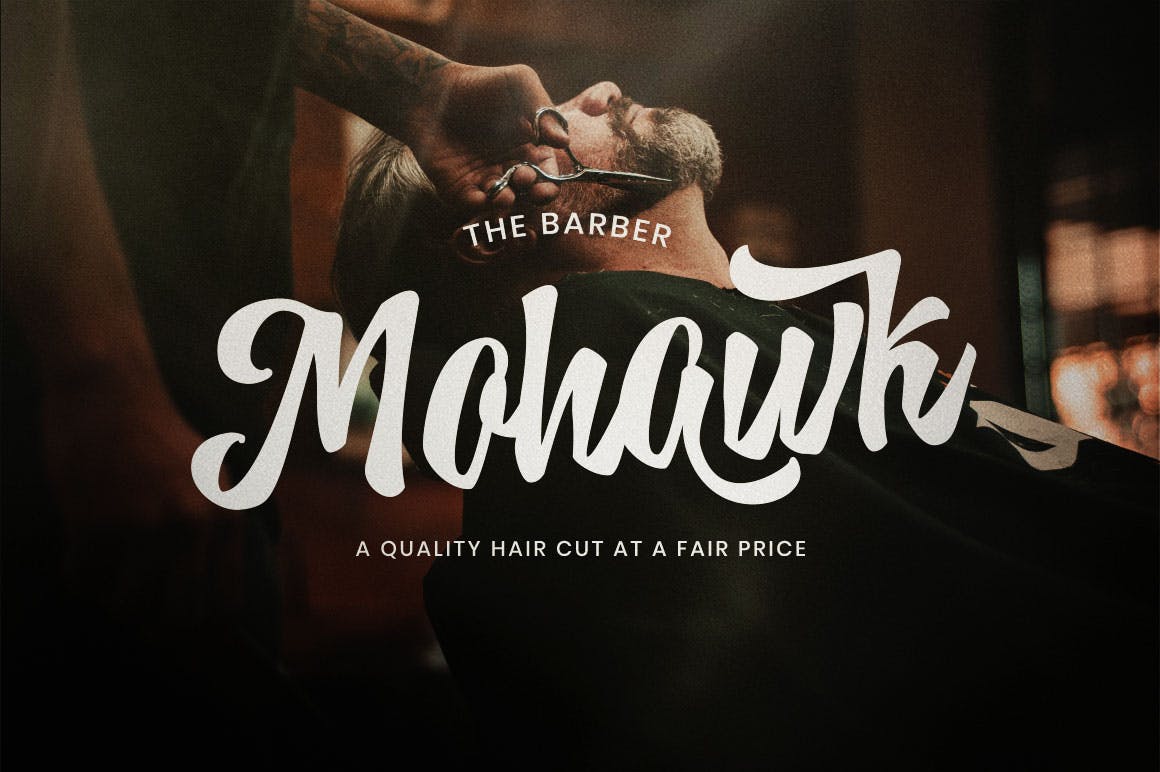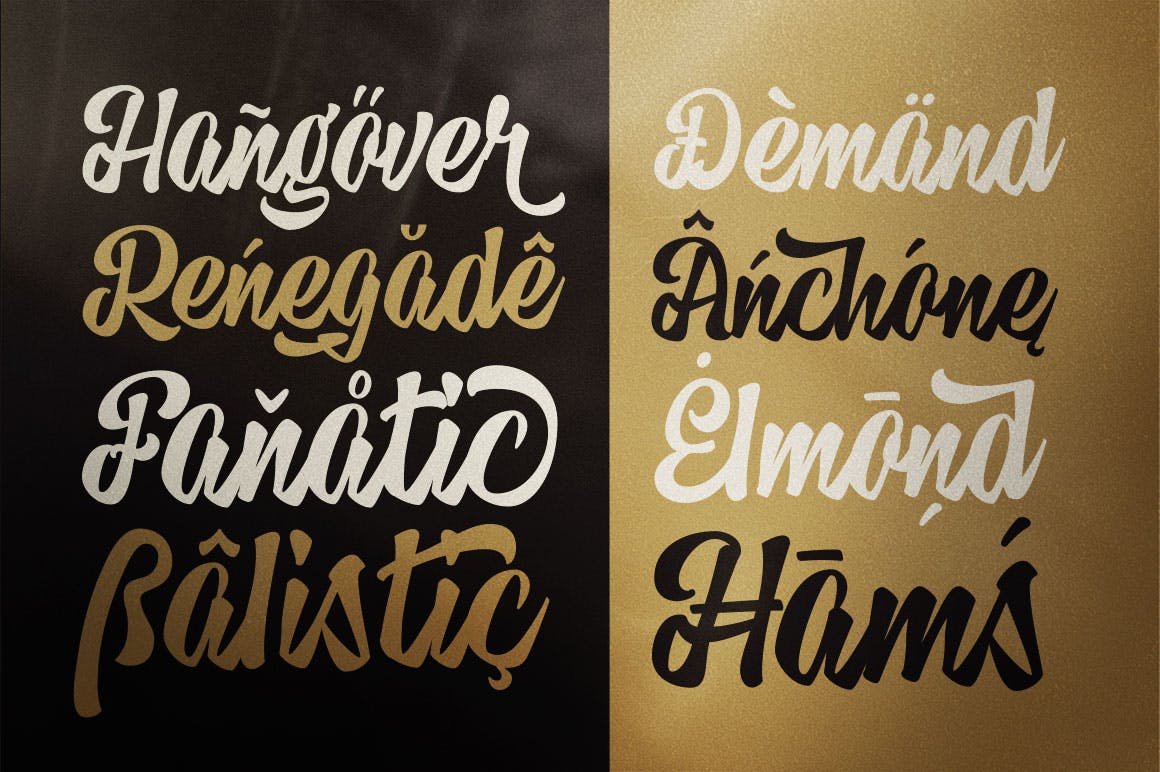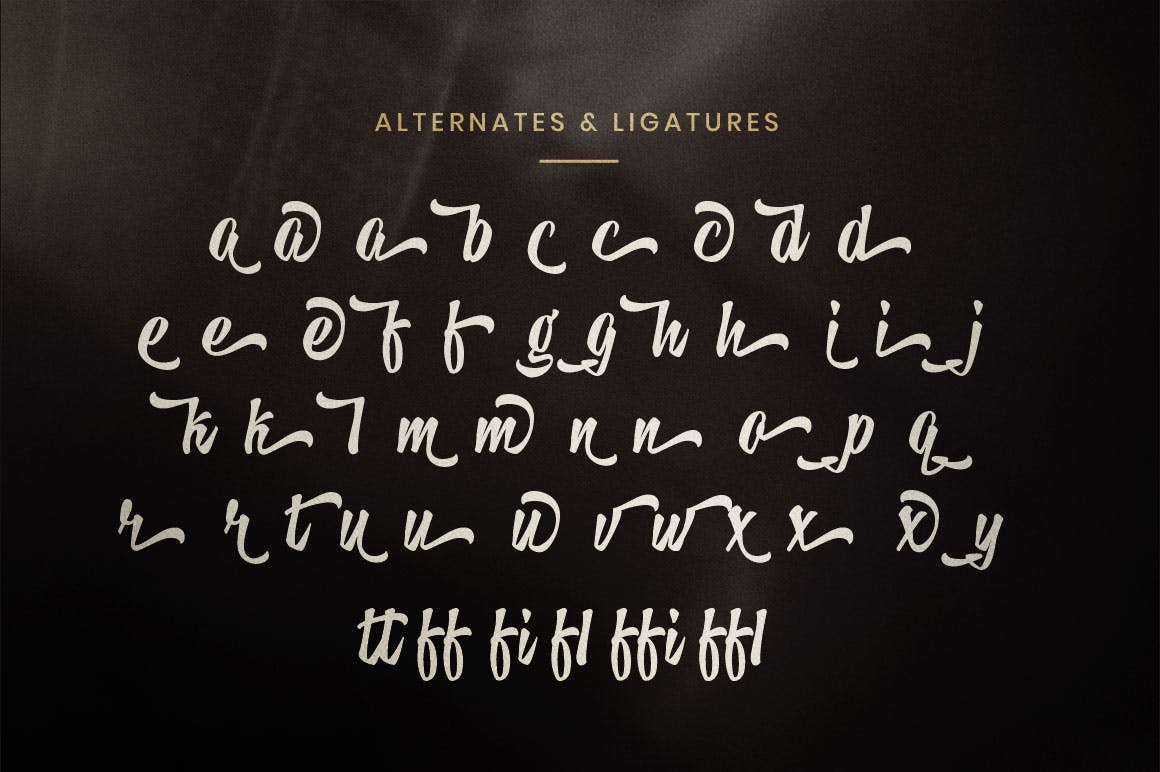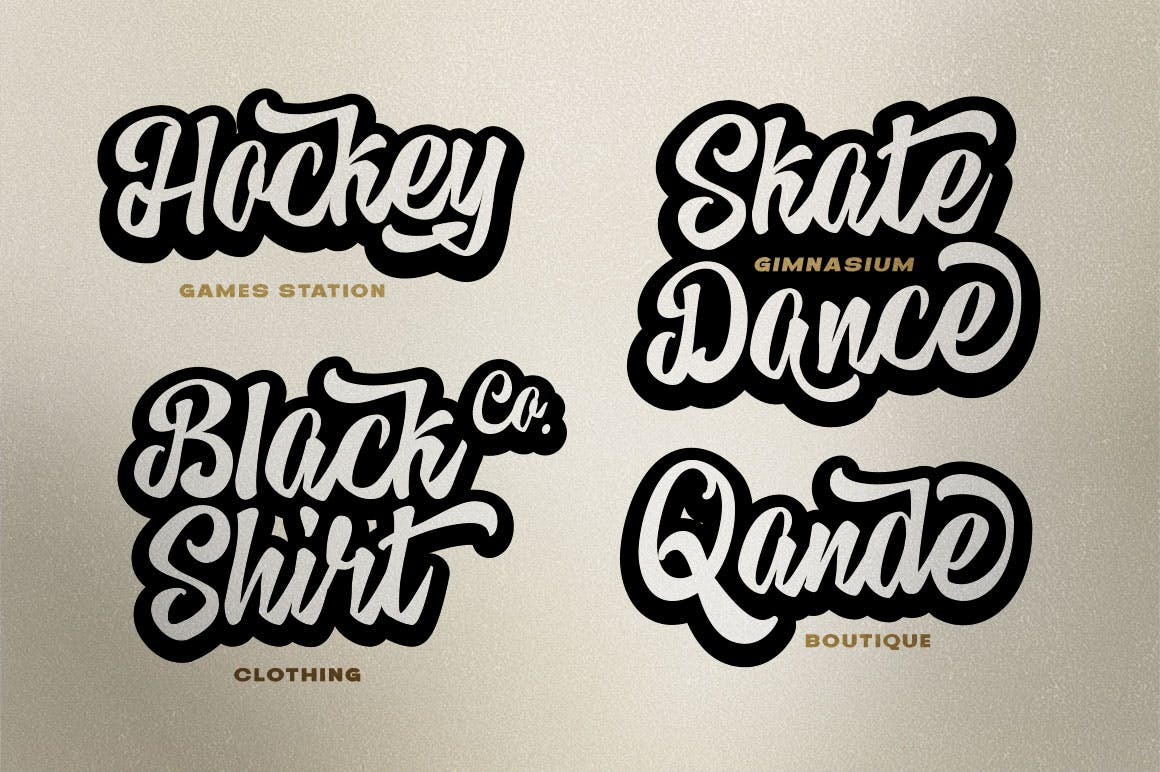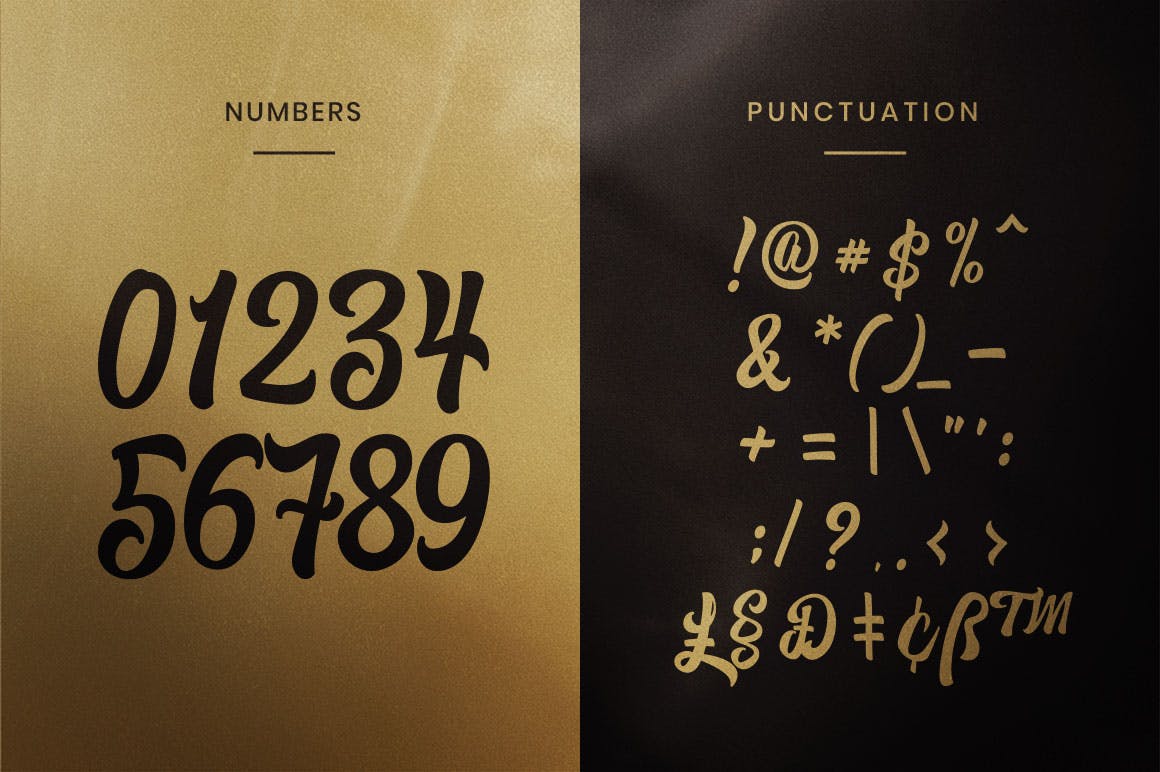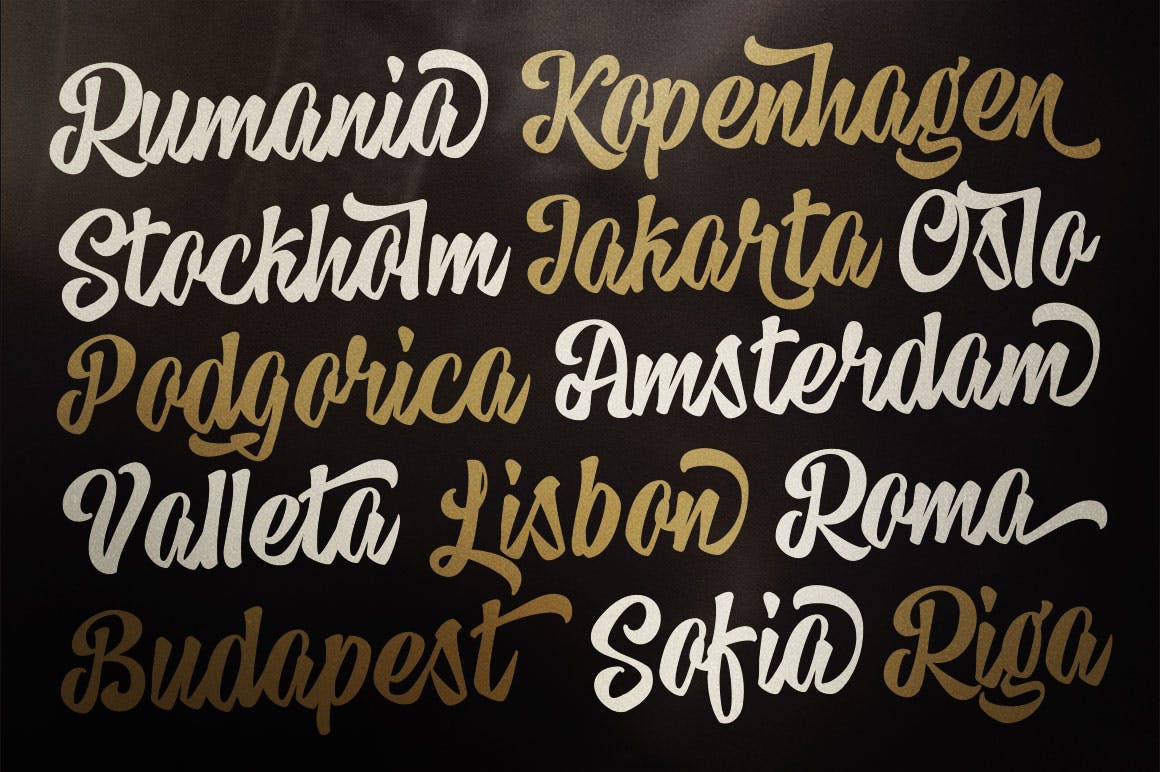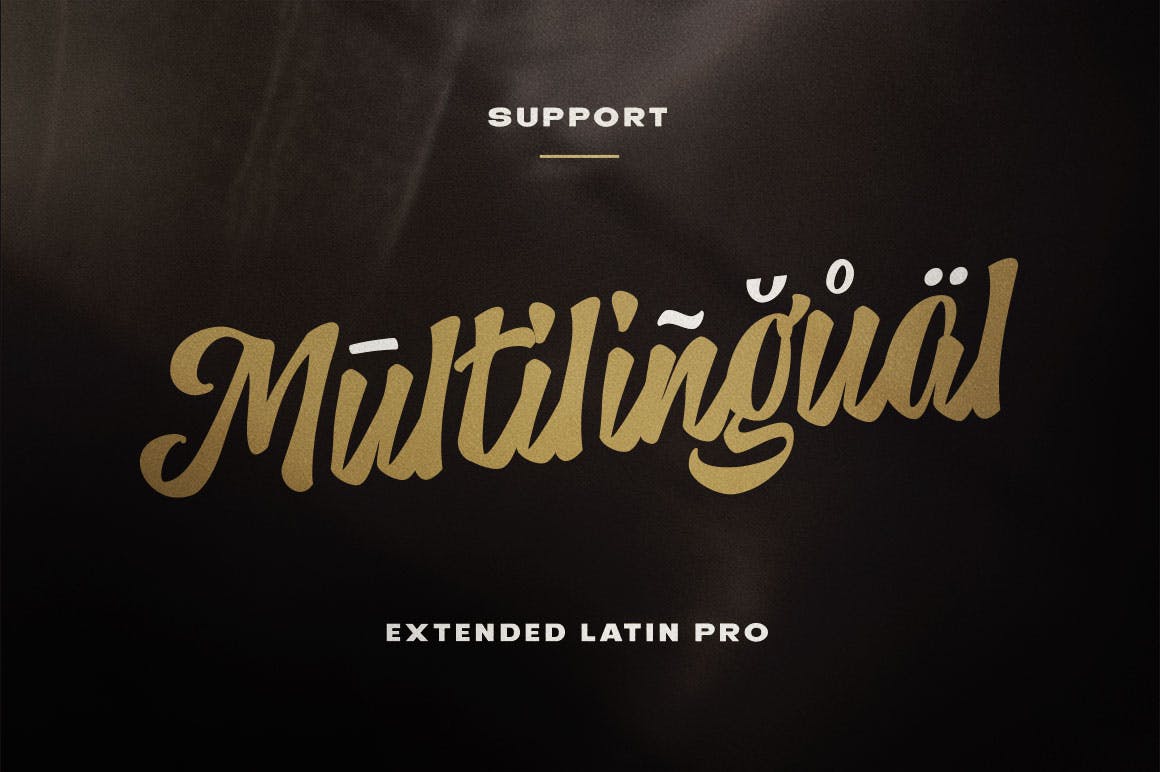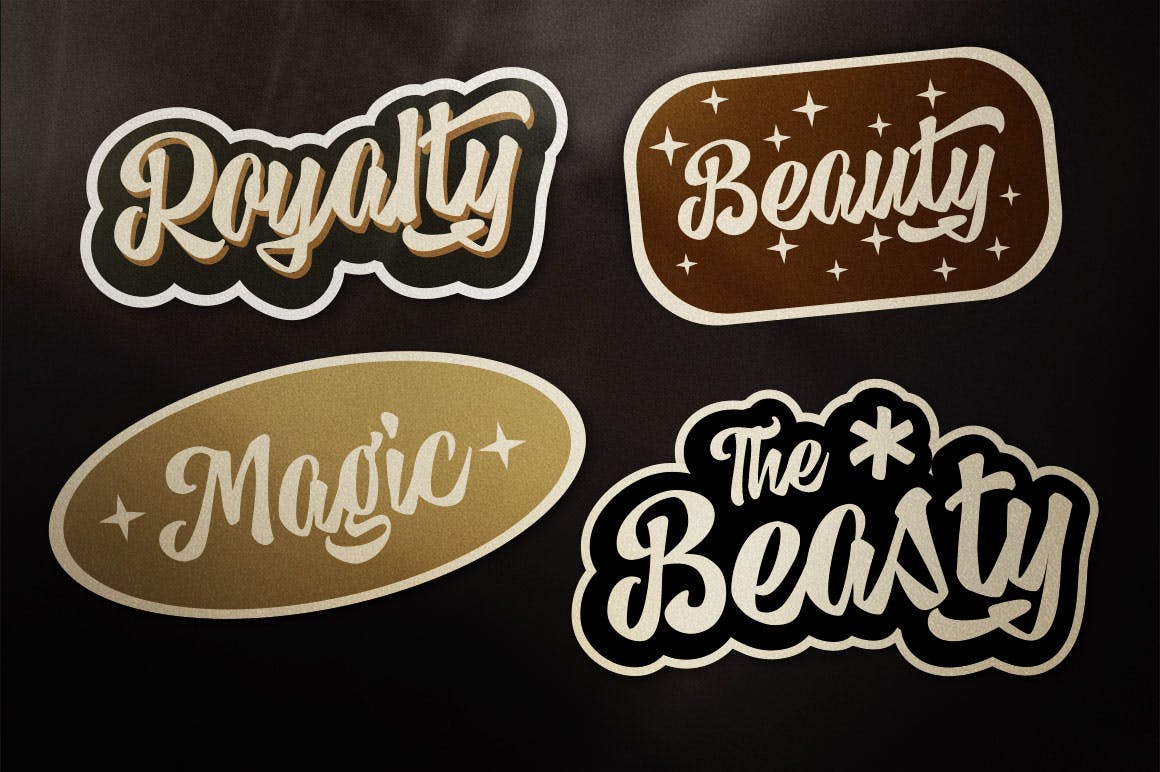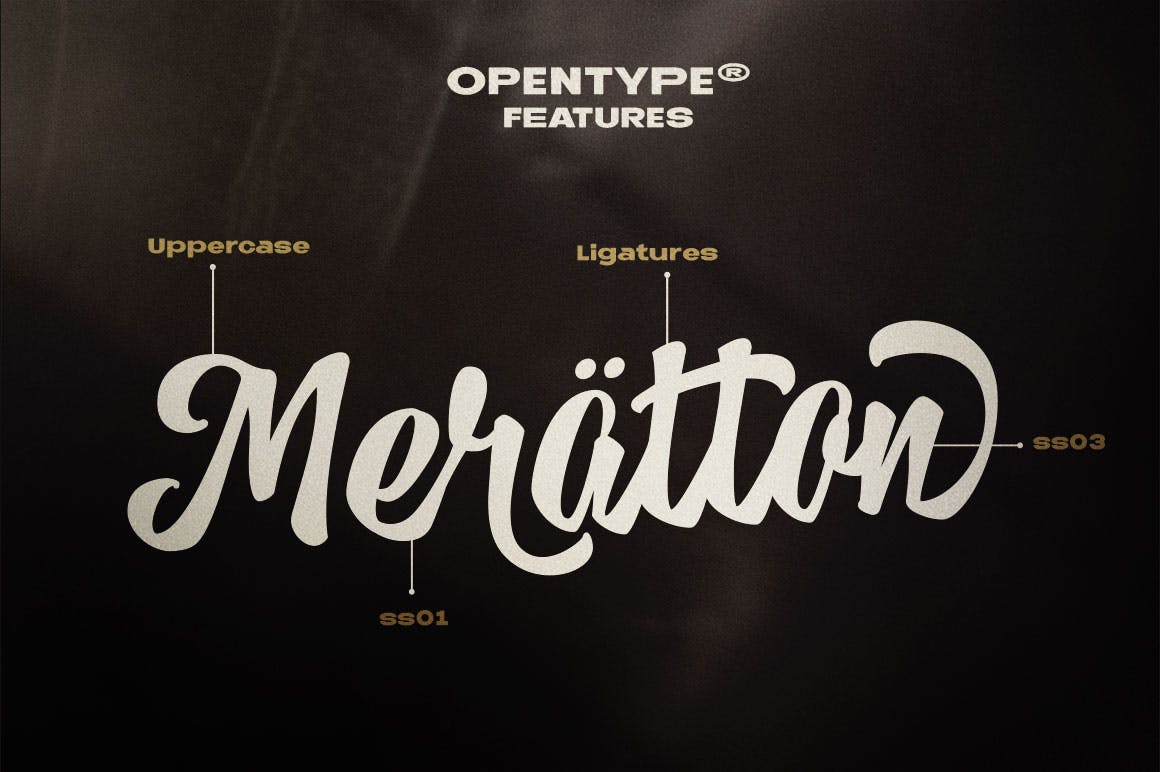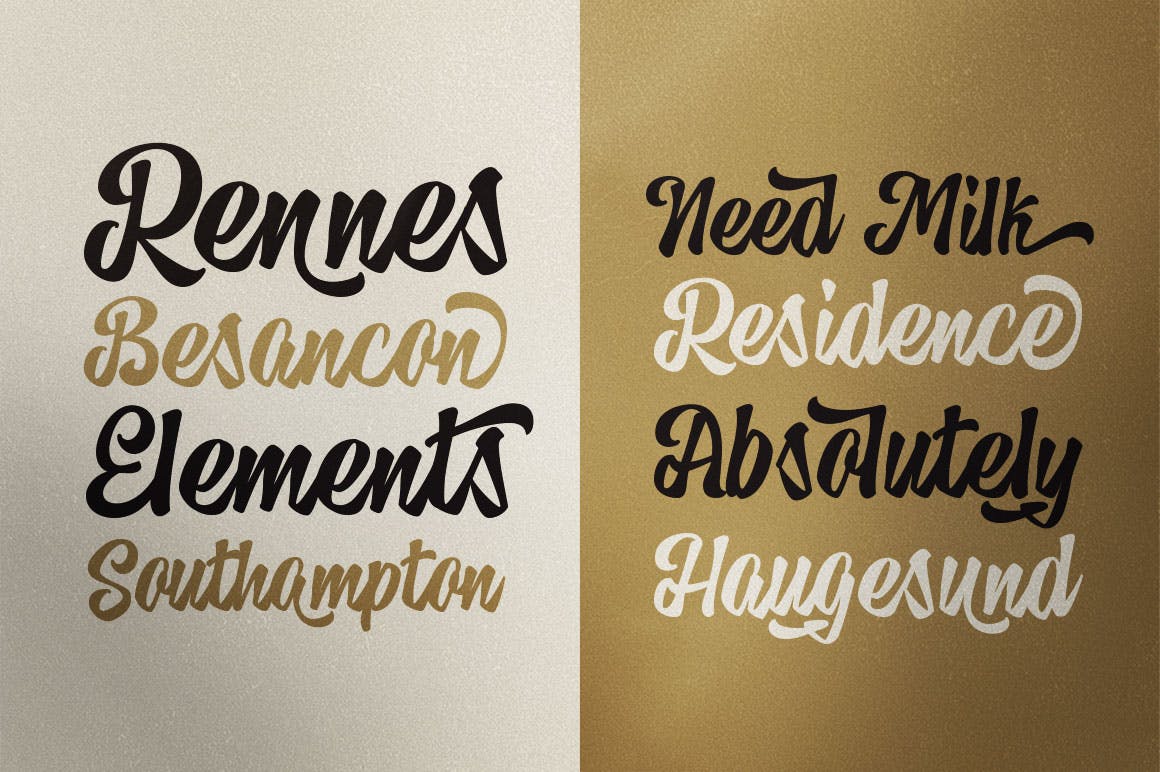
فونت Hedgehock Script با الهام از سبک نقاشی تابلو و ترکیبی از سبک نوشتاری دستی طراحی شده است. هر منحنی این فونت با دقت و شخصیت خاصی ساخته شده است. امیدوارم این فونت شما را در کارهایتان الهامبخش باشد. یک خط پایه بسیار جذاب دارد و بهخوبی با یک فونت ماژیکی مکمل جفت میشود. این فونت ایدهآل برای طراحی لوگو، نقلقولهای دستنویس، بستهبندی محصولات، هدر، پوستر، کالاهای تجاری، رسانههای اجتماعی و کارتهای تبریک است.
ویژگیهای OpenType